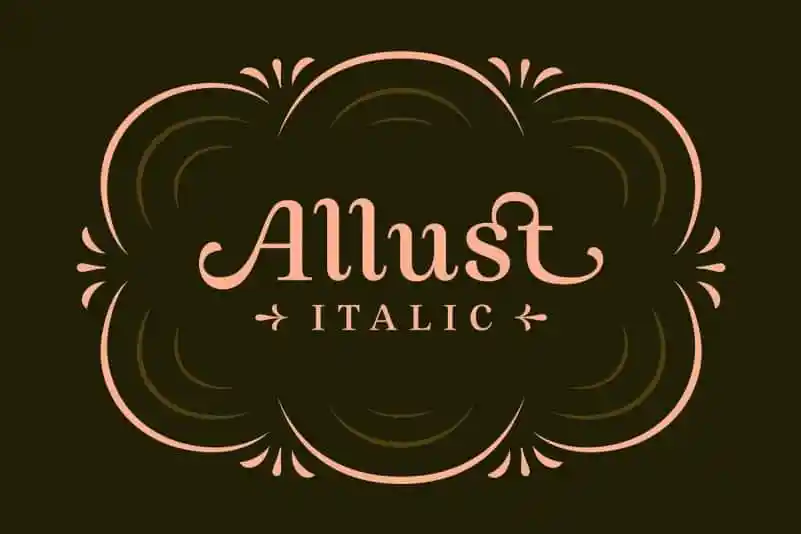
Introduzimos a Allust Serif Font, uma tipografia para exibição com personalidade única e expressiva, resultante das formas orgânicas e elegantes inspiradas em tipos transicionais espanhóis do século 18. Desenvolvida desde 2016, sua criação foi impulsionada por um desafio de transformar uma tipografia reta em italic inspirada nas artefácios chamigraficos, dando à fonte a capacidade de ser usada tanto para títulos quanto para textos curtos. Inspirada em formas orgânicas e elegantes, esta fonte é perfeitamente adequada tanto para destaque quanto para texto breve ou longo. Seu design delicado e expressivo se encaixa harmoniosamente em diferentes ambientes gráficos, desde revistas de jornal até cartazes publicitários, tornando-se uma escolha inteligente para qualquer projeto que valoriza elegância clássica combinada com modernidade.